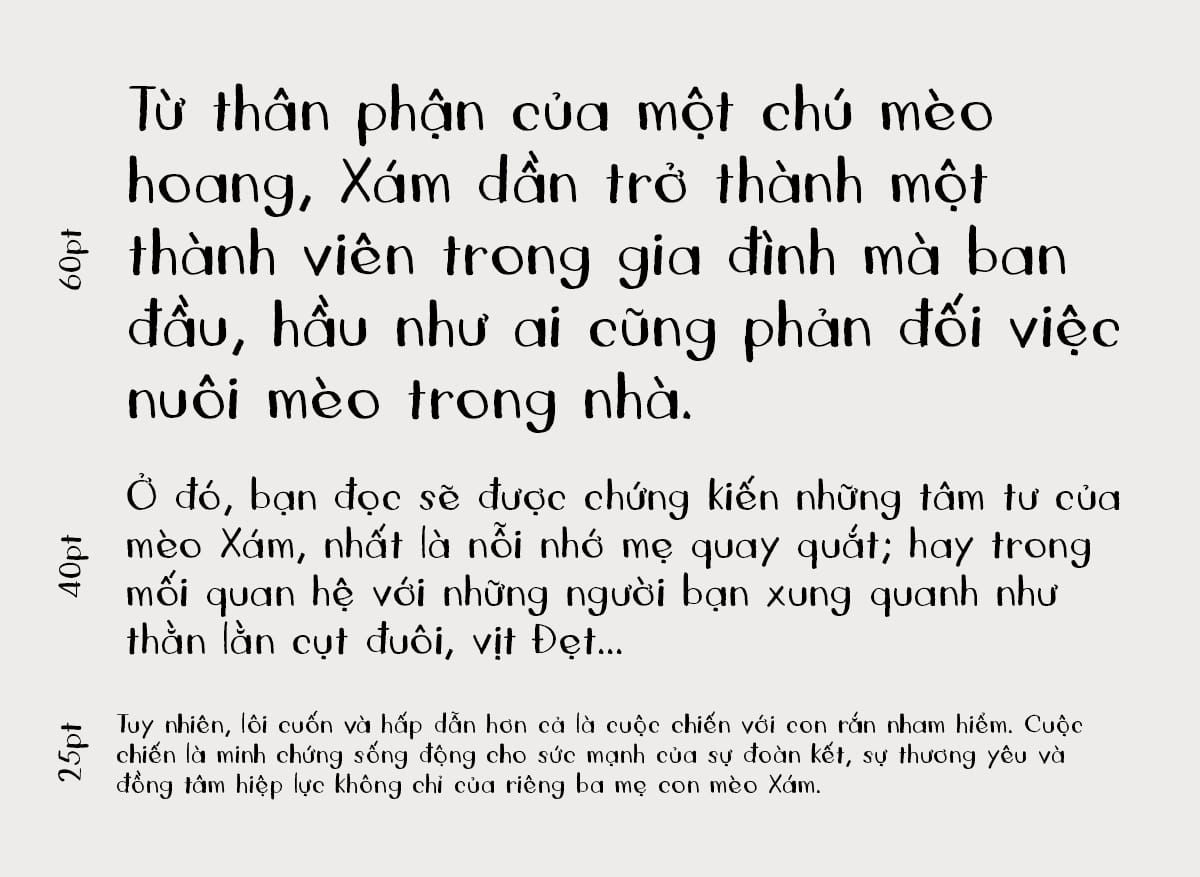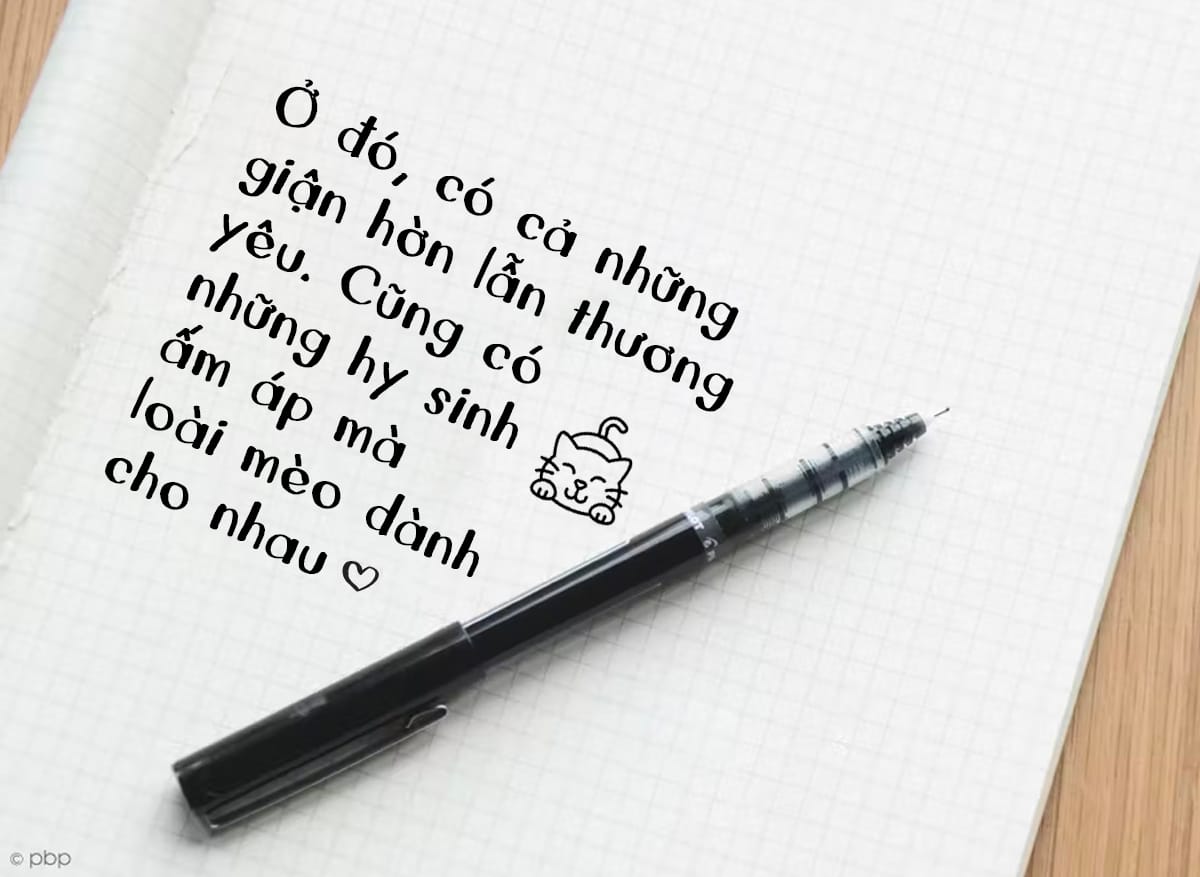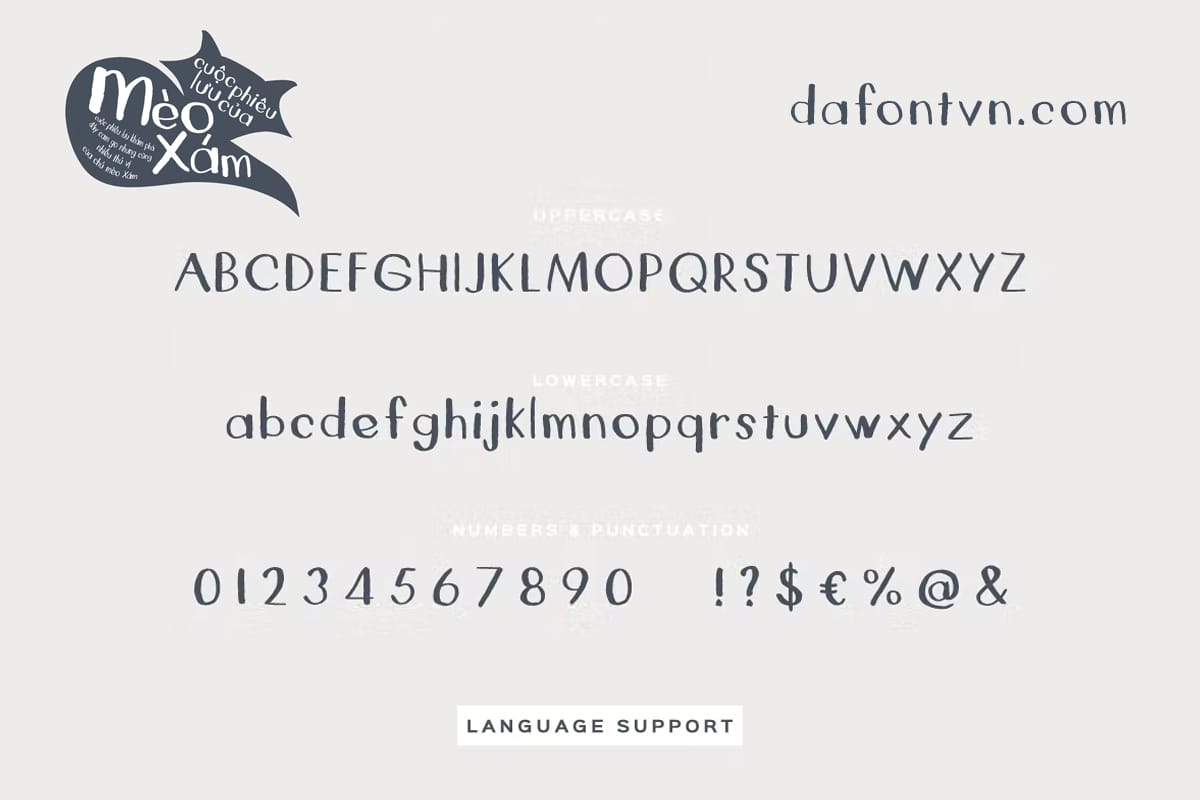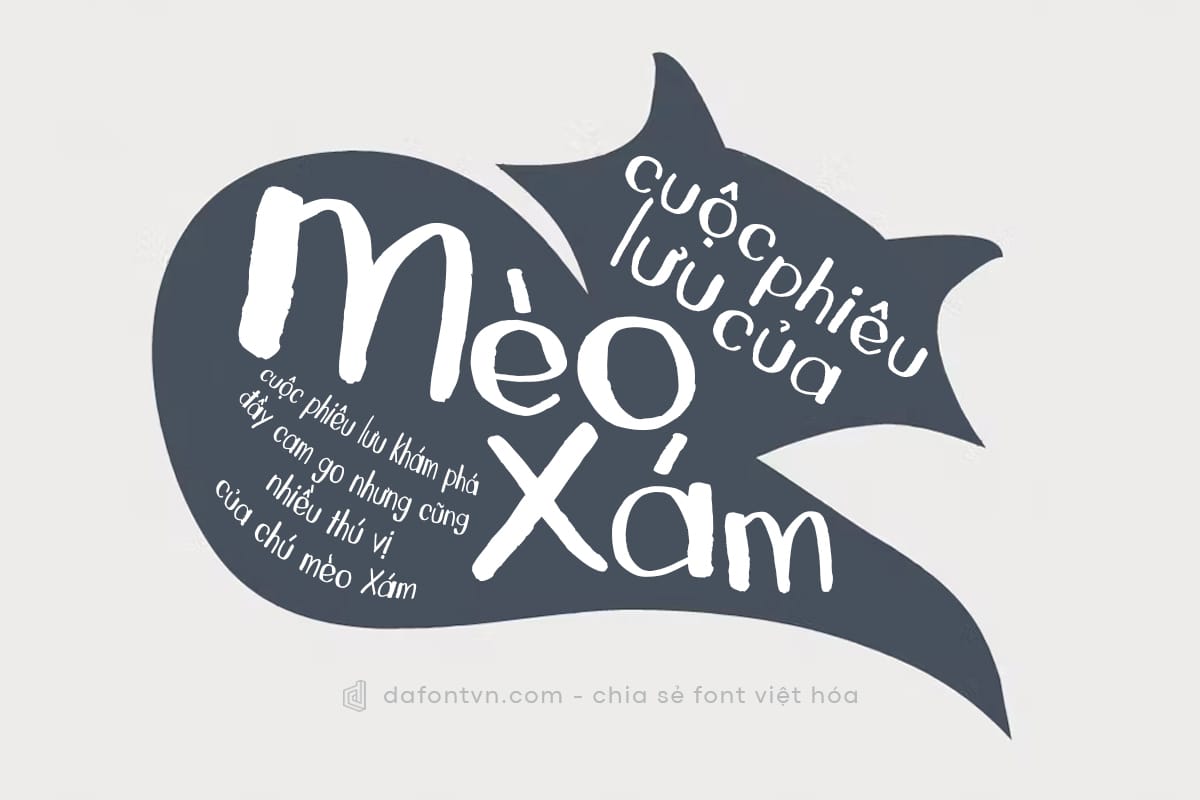
Lazy Fox là một font chữ lấy cảm hứng từ chữ viết tay, mang phong cách của các nét chữ bút lông phù hợp cho các thiết kế văn bản viết tay, bìa sách, thiệp mời, typo hoặc bất kỳ thiết kế nào, bao gồm chữ hoa và chữ thường được việt hóa đầy đủ.